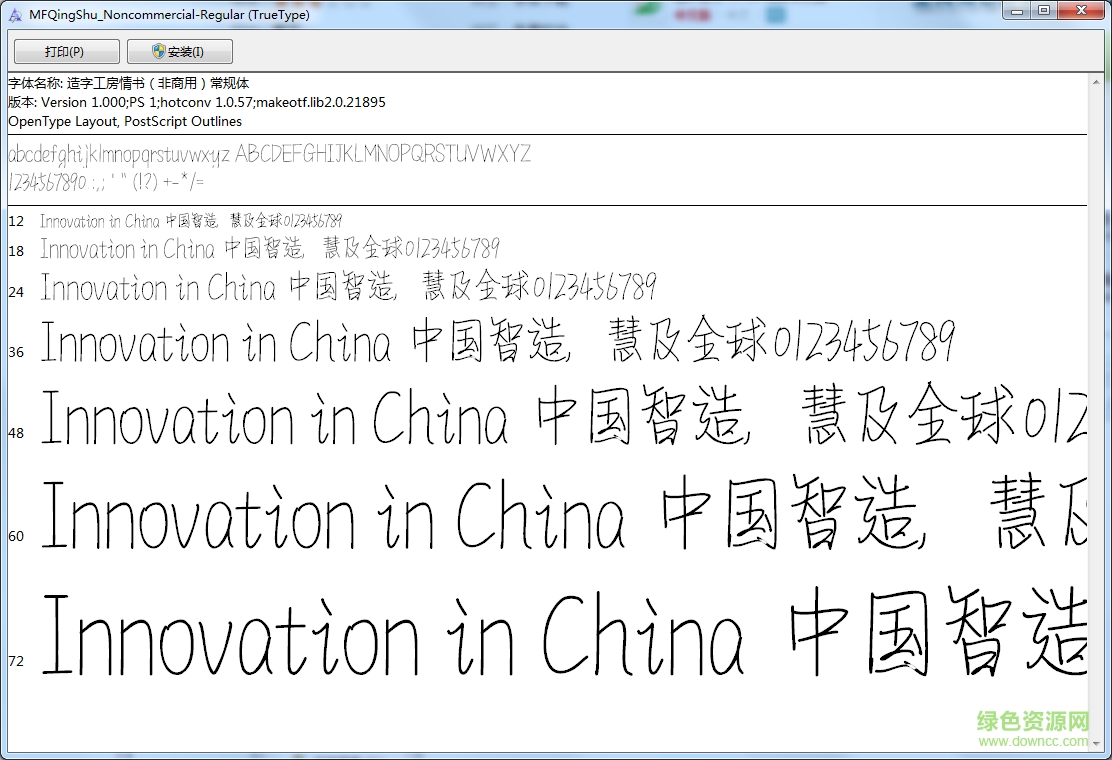
造字工房情書體由造字工房字體設(shè)計師成瑜歷時半年書寫完成,其字形俊秀、遒勁有力,優(yōu)雅中透出知性的氣息。文從字順,字形筆畫柔美俊秀、剛?cè)岵Y(jié)構(gòu)自然灑脫,充滿活力朝氣的青春氣息,完美呈現(xiàn)了手寫漢字之美,具有很強的自由應(yīng)用性。適用于廣告、信函或正文用字。
本字體為簡體字庫,采用OpenType/CID 格式, Adobe-GB1-5編碼?;谥腥A人民共和國GB2312-80字符集標(biāo)準(zhǔn), 另按需添加了 103 個漢字。共收容字數(shù) 6866 CJK 漢字,ASCII常用字符100個。